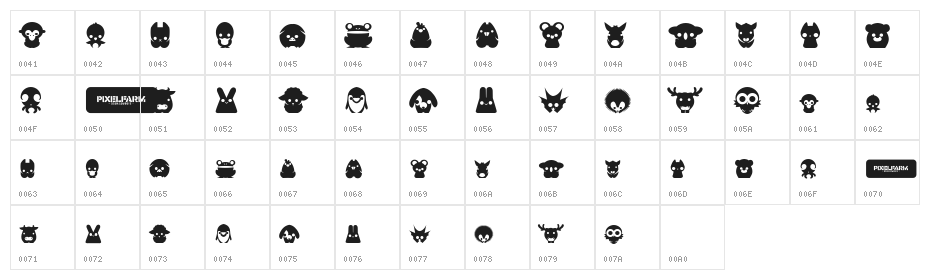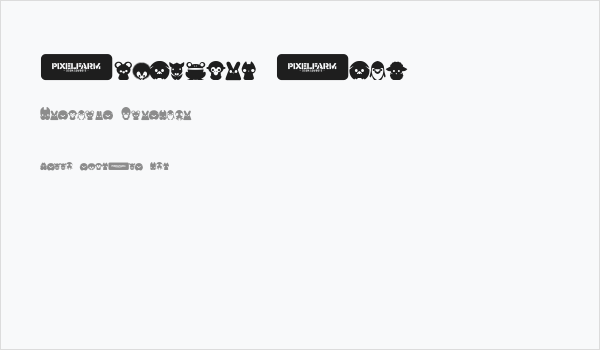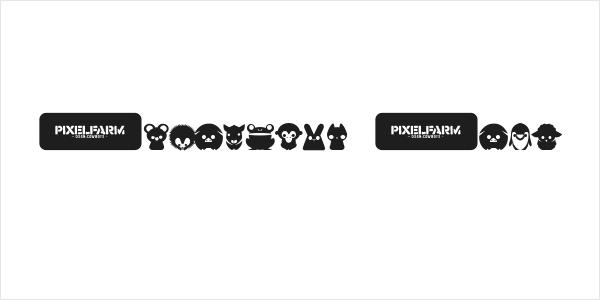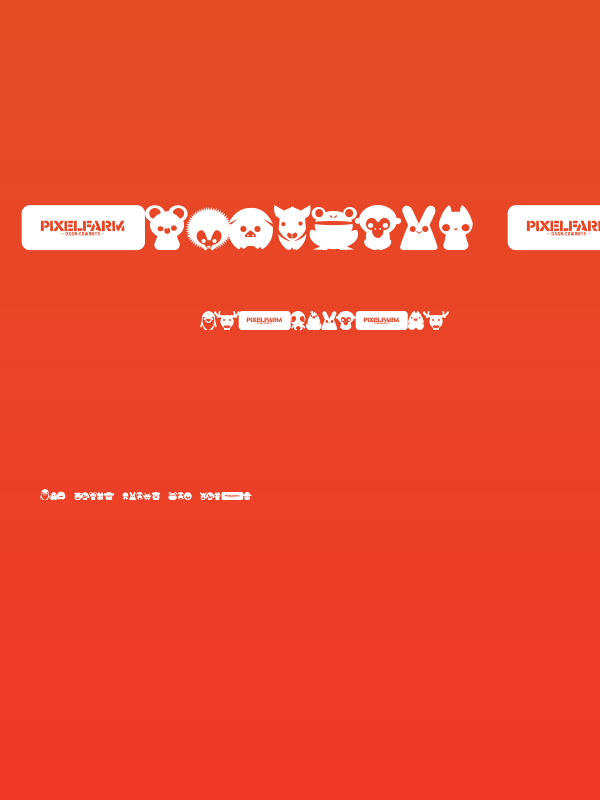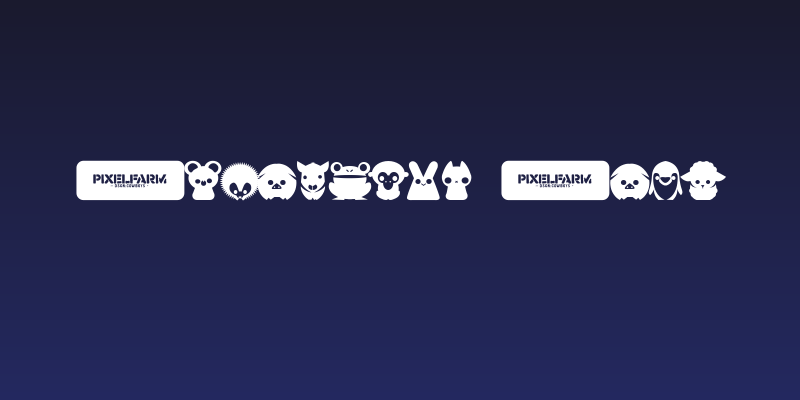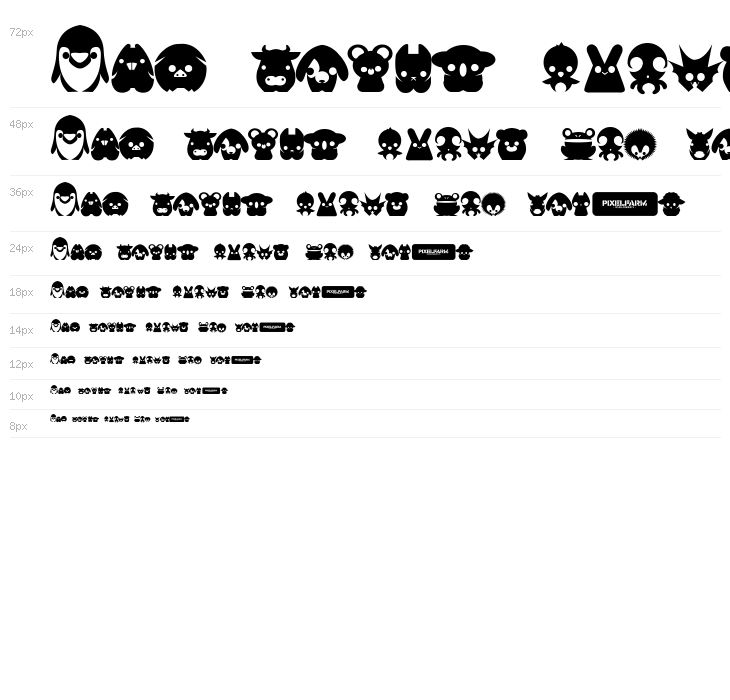
Pixelfarm Pets Font
| Stile generale | Playful, Decorative, Whimsical |
| Caso d'uso | Logos, Headlines, Posters, Children’s content |
| Progetti proposti | Children’s books, educational materials, pet shop branding, playful posters, party invitations. |